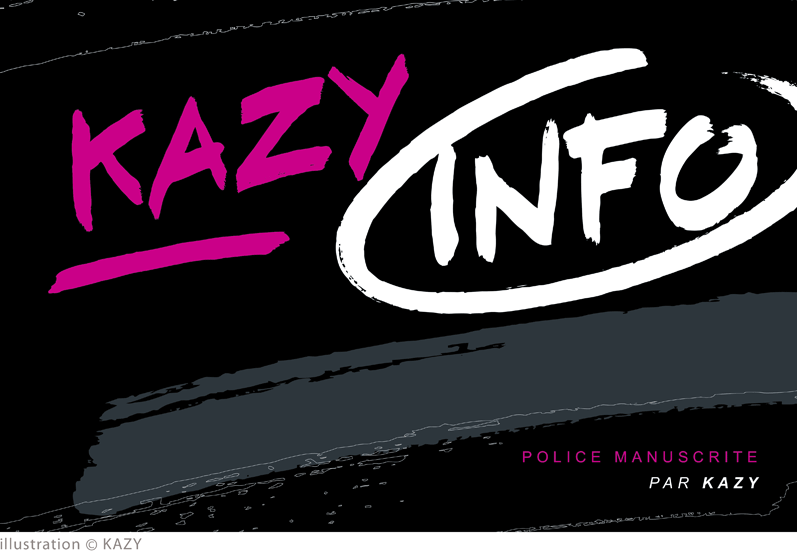
Preview and download Kazyinfo Font. Created by Emmanuel Didier in Script Brush styles with Free for personal use license.
KAZYinfo est une police manuscrite avec accents r�alis�e au feutre marqueur pointe plate avec un l�ger effet bross�. Cette police accompagnera parfaitement un large �ventail de design en renfor�ant leur dynamisme. Vous pourrez �galement profiter de quelques symboles pour animer vos cr�ations. Comme indiqu�, KAZYinfo est une police gratuite uniquement dans le cadre d�un usage personnel. Pour ce type d�utilisation, vos dons sont vraiment appr�ci�s. Vos projets personnels avec commission ou profit ne sont pas autoris�s sans licence. Pour une utilisation commerciale, vous trouverez la version de KAZYinfo avec licence ici : https://www.creativefabrica.com/designer/kazy __________ KAZYinfo is a handwritten font with accents made with a flat point marker pen with a slight brushed effect. This font will go perfectly with a wide range of designs by reinforcing their dynamism. You can also take advantage of some symbols to animate your creations. As noted, KAZYinfo is a free font for personal use only. For this type of use, your donations are really appreciated. Your personal projects with commission or profit are not allowed without a license. For commercial use you will find the licensed version of KAZYinfo here: https://www.creativefabrica.com/designer/kazy |